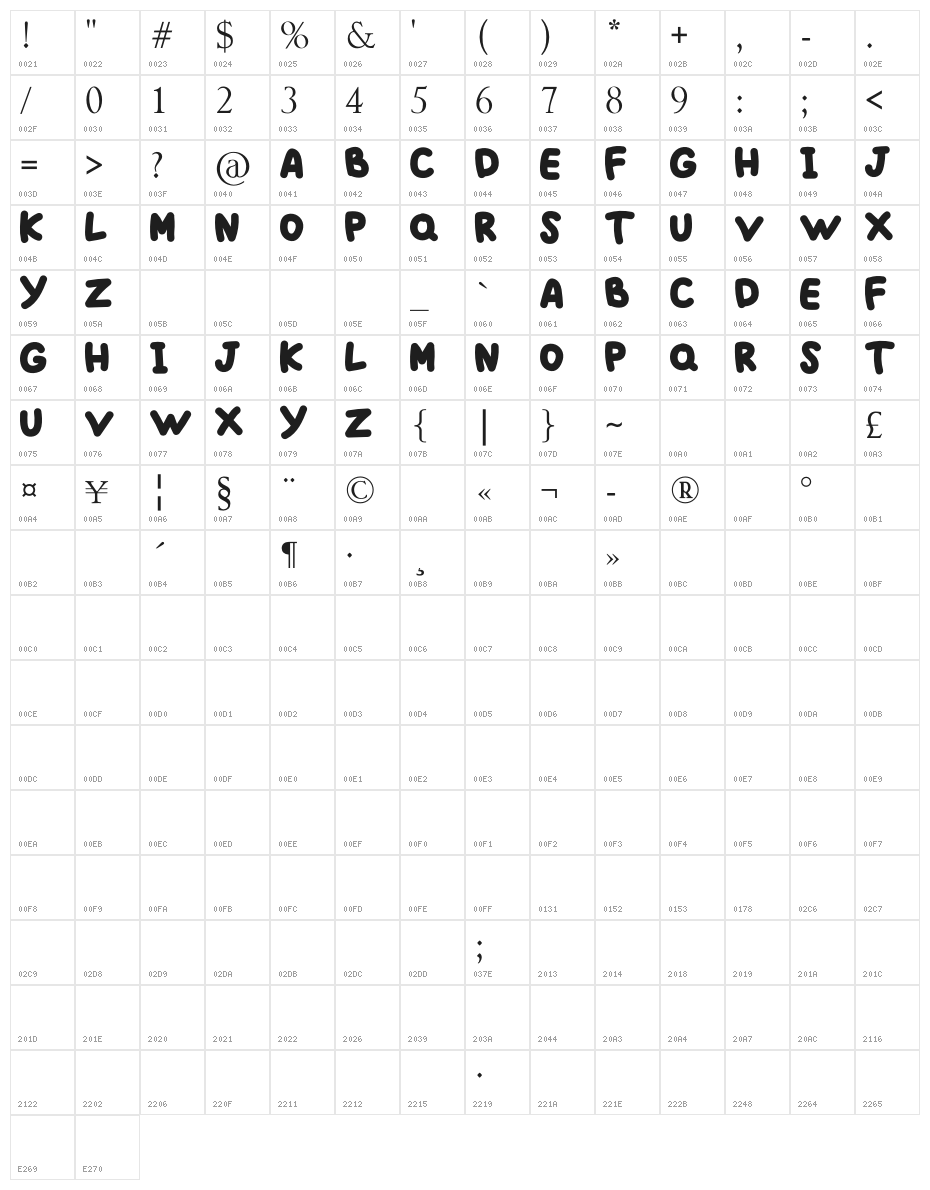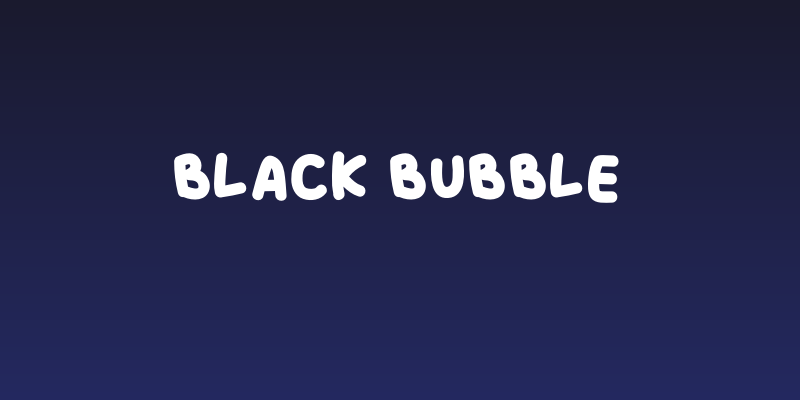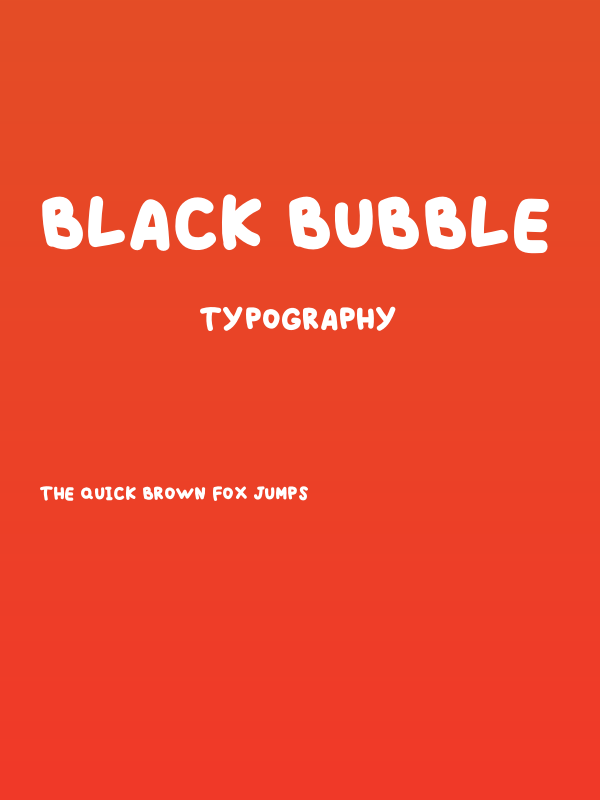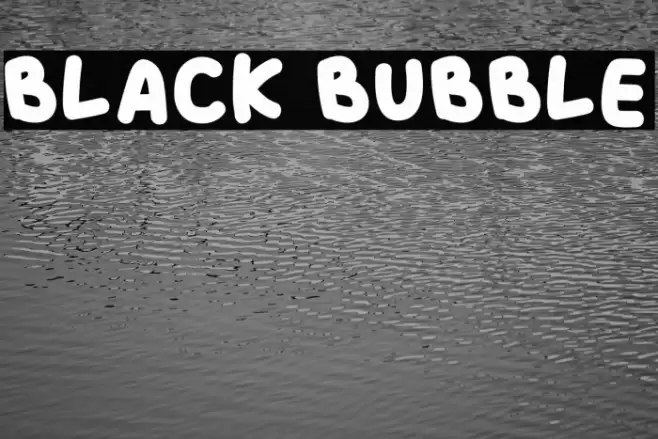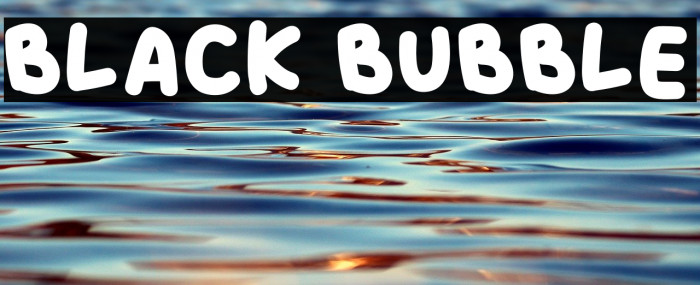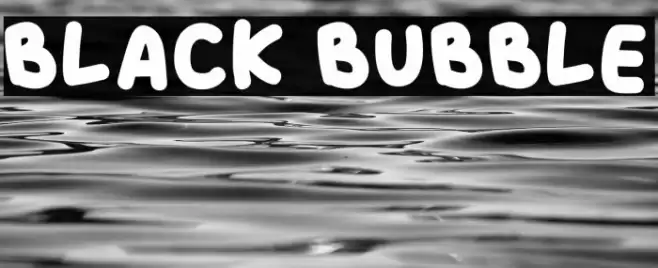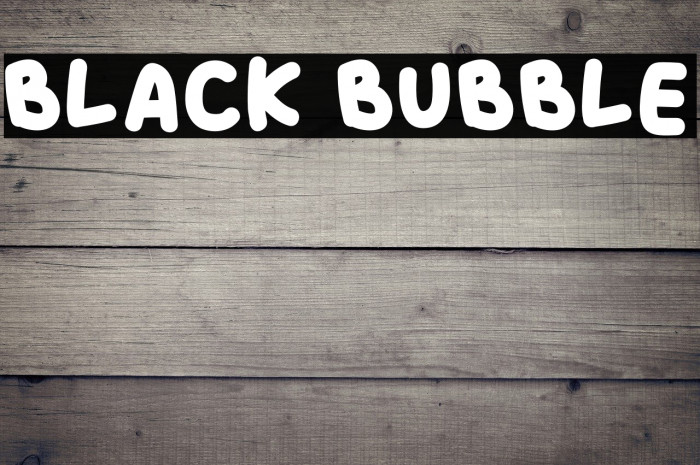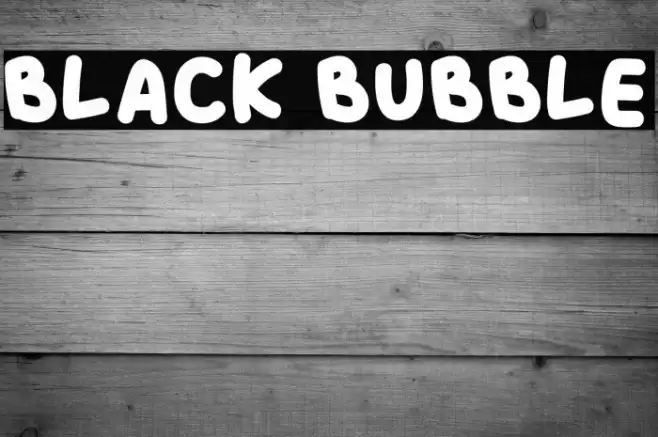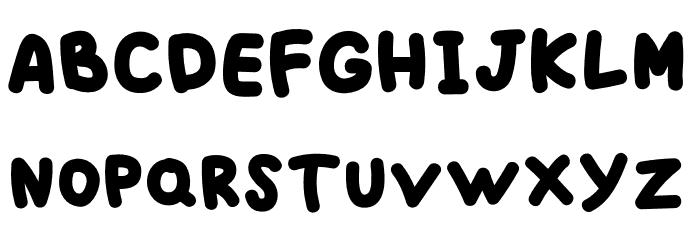
BLACK BUBBLE Font
| Stil general | Playful, Whimsical |
| Caz de utilizare | Headlines, Logos, Creative projects |
| Proiecte propuse | Ideal for children's books, playful branding, casual invitations, and creative projects. |